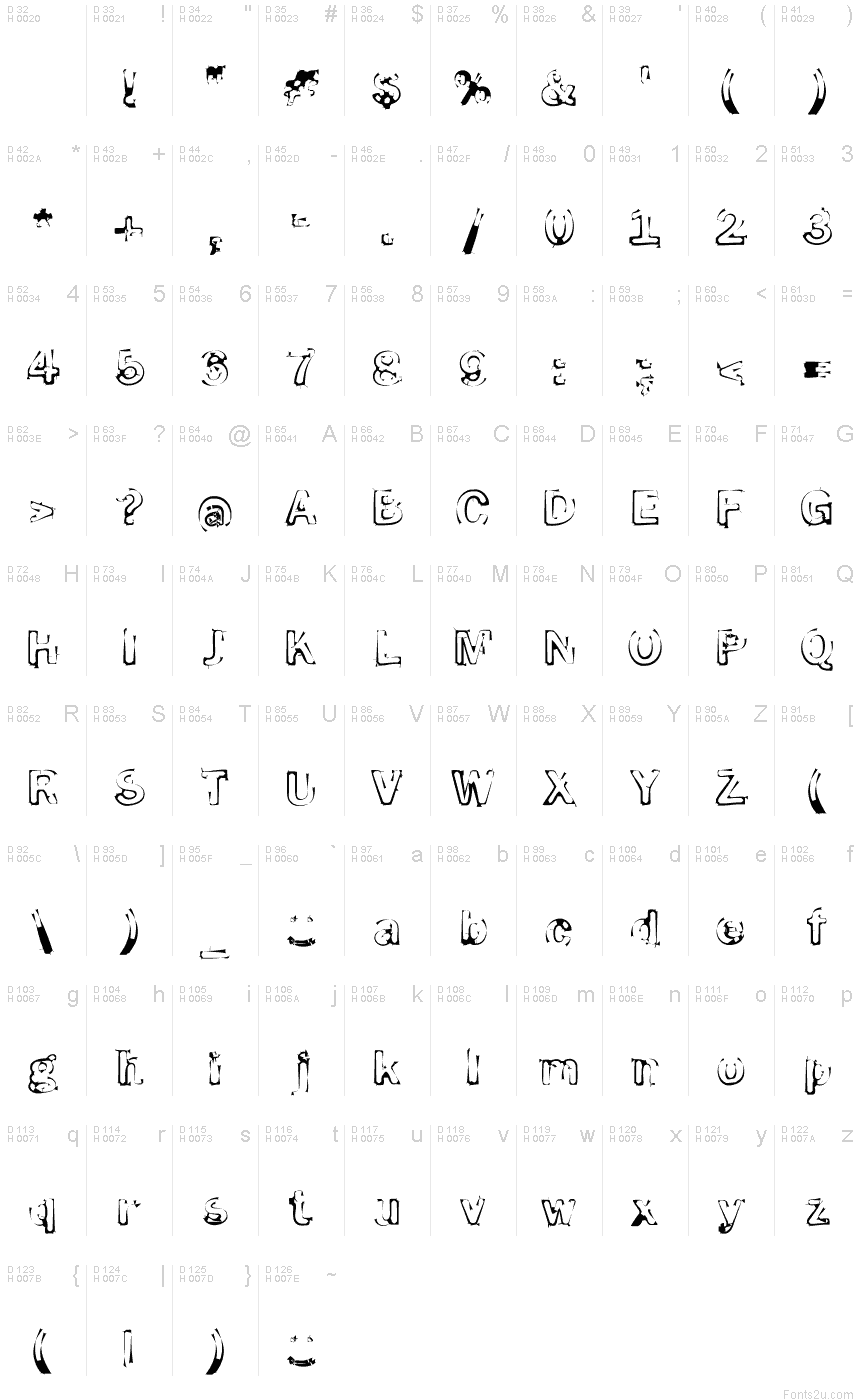
Smoke-Disturbed-Light
خط Smoke Disturbed Light من CybaPee Creations هو خط عرض مجاني بإطار دخاني. تبدو الحروف كأنها محترقة أو ذائبة أو مشوهة بفعل الحرارة. تمنح المنحنيات ذات الطابع القروسطي والحواف المشققة المتموجة الحروف طابعاً قلقاً ومحترقاً، حيث يبدو الأسلوب أقرب إلى الدخان المتصاعد منه إلى مجرد تشويه بسيط.
هذا الخط المجاني مناسب للملصقات، وعناوين أفلام الرعب، ومنشورات الهالوين، وأغلفة الألبومات، وعناوين الألعاب، والعلامات التجارية القصيرة حيث يمكن للإطار الدخاني أن يبرز بوضوح. يعمل الخط بشكل أفضل في العبارات القصيرة والمواقف التي تتطلب تميزاً بصرياً، خاصة في الشعارات أو العناوين التي تحتاج إلى أجواء احتراق قلقة دون أن تتحول إلى كتلة صلبة ثقيلة.